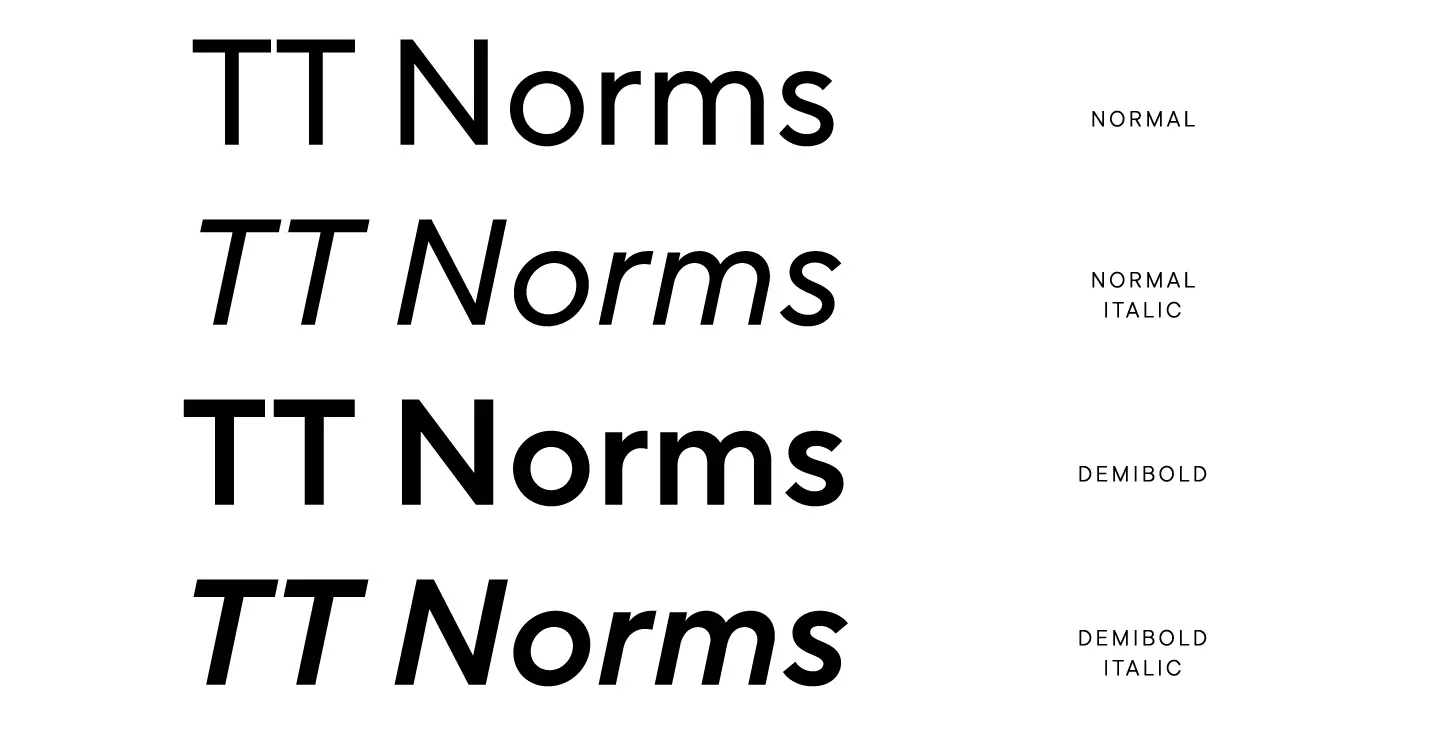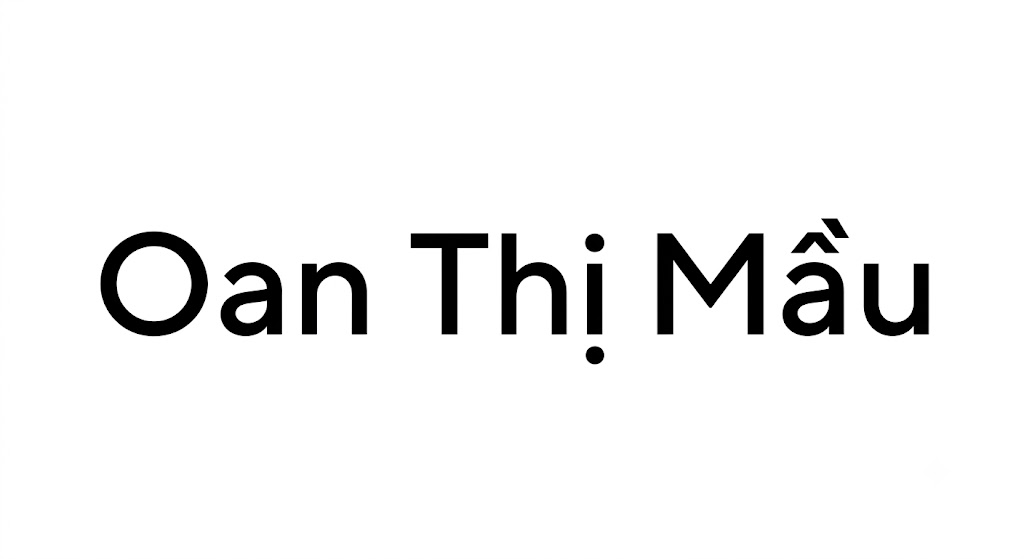
Font TT Norms Pro Việt hóa là bộ phông chữ không chân (Geometric Sans-serif) thuộc hàng kinh điển trong giới thiết kế hiện đại, được sáng tạo bởi xưởng đúc chữ TypeType (Ivan Gladkikh và Pavel Emelyanov). Được mệnh danh là một trong những phông chữ hình học đa năng và trung tính nhất thế giới, TT Norms Pro sở hữu dải biến thể đồ sộ từ Thin thanh mảnh đến TT Norms Pro Black cực đậm. Doozypack.vn cung cấp link tải trọn bộ chuẩn kỹ thuật, giúp bạn sở hữu TT Font chất lượng cao, hỗ trợ đầy đủ tiếng Việt để tự tin thiết kế bao bì và bộ nhận diện thương hiệu chuyên nghiệp.
Đặc điểm thẩm mỹ độc đáo của bộ font TT Norms Pro
TT Norms Pro không đi theo sự phô trương rườm rà; sức mạnh của nó nằm ở tính kỷ luật của hình khối, sự minh bạch tuyệt đối và khả năng thích ứng hoàn hảo trong mọi không gian thiết kế.
Phong cách Geometric Sans-serif chuẩn mực và trung tính
Đặc trưng lớn nhất của Font TT Norms Pro Việt hóa là cấu trúc chữ dựa trên các khối hình học cơ bản nhưng được tinh chỉnh tỉ mỉ để mắt người đọc cảm nhận sự mềm mại, tự nhiên. Thân chữ thẳng đứng kiêu hãnh, các nét vẽ có độ dày đồng đều tạo nên một nhịp điệu Typography vô cùng ngăn nắp và chuyên nghiệp. Phông chữ này mang lại cảm giác minh bạch, uy tín, rất phù hợp với các tập đoàn lớn và các thương hiệu cao cấp.
Hệ sinh thái biến thể đồ sộ từ Thin đến TT Norms Pro Black
Một lý do khiến các designer luôn săn đón TT Font chính là hệ gia đình phông chữ vô cùng phong phú. Biến thể TT Norms Pro Black sở hữu độ dày nét cực lớn, tạo ra trọng tâm thị giác áp đảo, là vũ khí hoàn hảo để làm tiêu đề chính trên nắp hộp quà tặng hoặc mặt trước túi giấy. Trong khi đó, các biến thể mỏng hơn lại tối ưu tuyệt đối cho phần nội dung mô tả chi tiết.
Ưu điểm nổi bật của bản Font TT Norms Pro Việt hóa
Khi ứng dụng các phông chữ hình học quốc tế vào thị trường trong nước, sự chỉn chu về dấu câu là yếu tố quyết định đến tính chuyên nghiệp của ấn phẩm:
- Khắc phục triệt để lỗi dấu tiếng Việt: Phiên bản Việt hóa đã được đội ngũ thiết kế trau chuốt thủ công từng dấu câu. Các dấu sắc, huyền, hỏi, ngã, nặng được vẽ với tỷ lệ cân đối, đặt ở vị trí thoáng đãng so với thân chữ, không gây cảm giác chắp vá hay đè nét làm mất tính thẩm mỹ hình học.